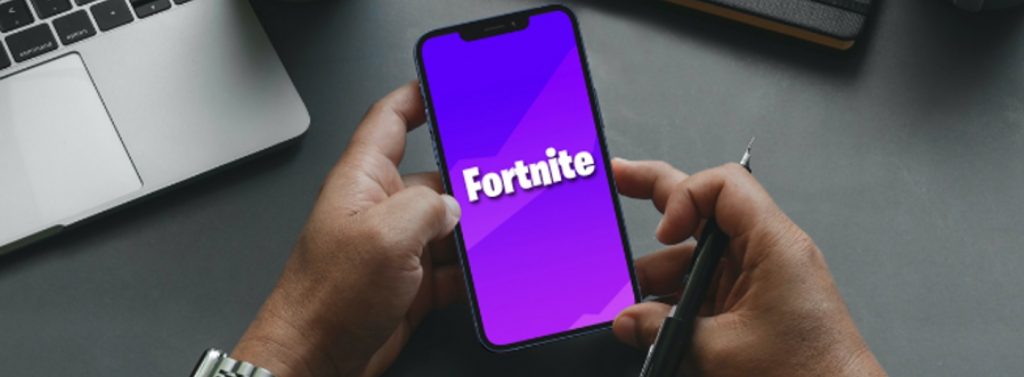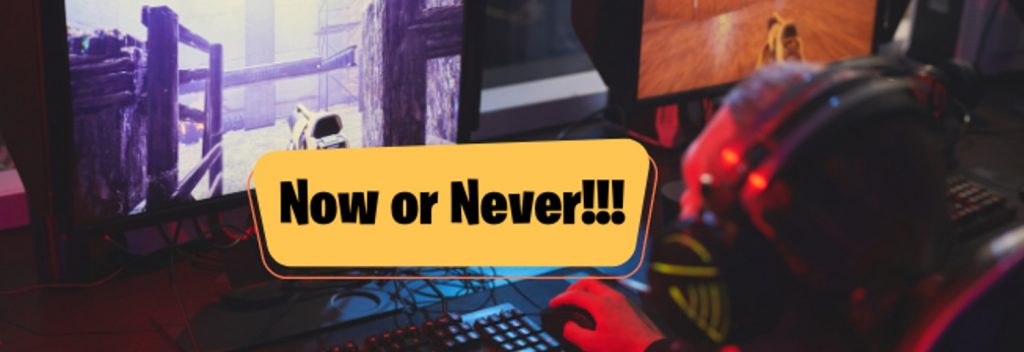
如何使用 Fortnite 字體創建漂亮的模型
已發表: 2022-11-22您是否多次聽到“Mockup”這個詞卻不知道這個詞的用途? 不要擔心,因為今天,我們將通過定義這個術語及其最佳字體來打破你的好奇心。 模型設計的成功在很大程度上取決於您所做的字體選擇。 字體越合適,您的設計就會越好。
在眾多選項中,我發現最完美的選項是 Fortnite,您以前可能也用過它。 本指南將討論有關此字體的所有重要因素。 除此之外,我們還將討論如何使用這種字體設計吸引人的模型。
什麼是模型設計?
模型是一種尚未發布的設計,只是一個樣本,用於展示最終產品在向公眾展示時的變化情況。 模型有多漂亮取決於您的專業知識。 您可以使用不同的可用軟件設計大量模型,包括 Photoshop 或 Adobe illustrator。 模型可以創建一個完整的網站,也可以是一個頁面。
他們最好的一點是,他們可以讓您自由地在需要的地方進行更改,因為一旦網站上線,就會出現並發症。 您還可以設計它們以在創建最終產品之前獲得公眾的反應。 它們被用於不同的領域,包括軟件開發、建築、消費品、家具等。
使用 Fortnite 字體製作模型
如果您是遊戲愛好者,您可能玩過 Fortnite 遊戲,該遊戲在發佈時獲得了所有好評。 2017 年,它被製作出來,超過 1 億人參與了該遊戲。 有了這次的成功,遊戲中使用的字體也獲得了讚賞,成為了大家的需求。 這款遊戲的標誌字體吸引了所有人的眼球,因為它很吸引人,並且具有吸引所有人注意力的力量。
經過研究,我們發現這款遊戲的標誌所使用的字體不是別人,正是Tal Leming多年前創造的Burbank Big Condensed。 而且,它是專門作為顯示字體創建的,非常適合這個原因。 它是一個大家族,有很多權重、樣式和字符,所以用在各種意義上的模型設計中都是很好的。
好吧,問題仍然存在,如何在看起來吸引人的設計中使用這種字體? 答案如下。
1. 將其用於品牌項目
假設您正在處理任何特定品牌,並且仍然對哪種字體最有希望用於模型設計感到困惑。 在這種情況下,您永遠不會被誤認為是 Fortnite 字體,因為它專門用於此驅動器。 它使品牌脫穎而出,人們不會停止重視您的工作。 這種字體為您的品牌帶來的優雅觸感也值得讚賞。
因此,如果你想開發一個立即吸引註意力的模型設計,我建議你在你的品牌作品中使用免費版本的 fortnite 字體,然後等待魔法。 這是您在排版方面獲得的最佳建議。
2.在徽標上使用此字體
眾所周知,Fortnite 在用於 Fortnite 視頻遊戲的徽標後積累了人氣。 因此,使用此字體的最佳方法是將其保存在重要的地方。 您可以將其保留在需要清晰的標題、徽標或有影響力的標題中。 這是您如何最好地使用這種字體。 在這種字體被淘汰後,許多設計師充分利用並在他們的設計中使用它,尤其是在標誌上。
同樣,如果您的品牌已準備好發布並且唯一的要求是徽標字體,請繼續使用 Fortnite,稍後您一定會感激您的決定。 這種 san-serif 字體提供清晰的可見性並吸引讀者關注您的設計。 在標題或徽標上使用此字體是將此字體用於精美模型設計的另一種最佳方式。
3.最適合遊戲平台
這種字體無疑是您的遊戲模型設計的最佳選擇,因為在 Fornite 遊戲發布後人們開始了解它,並且每個人都為之瘋狂。 如果你有一個遊戲網站,你不應該再考慮這種字體是否適合設計。 去吧。 充分利用這個大字體系列,讓結果對您有利。
4.根據設計心情選擇
選擇一種完美無瑕的字體非常適合設計氛圍,因為如果您的字體不能與設計相得益彰,那麼您的模型將是最大的失望。 作為一名設計師,你必須知道哪種字體適合不同類型的設計,並通過實踐,成為這項技能的高手。 Fortnite 字體的主要品質之一是它適合不同的心情; 這就是為什麼在不同的設計中使用它之前不需要考慮太多。
如果你想讓你的 Mockup 設計成功,必須注意這一點,以便讀者在檢查你的設計時順其自然。
5.注意配對
配對對於成功的設計也很重要,所以一定要做好。 在一個設計中,你至少需要 2 或 3 種字體,所以它們都應該非常適合,這樣它們看起來才不會很奇怪。 該遊戲徽標上使用的字體與擴展的 Burbank Big 字體家族相同,因此您一定會得到類似的字體。
此外,它是一種 san-serif 字體,因此您還可以找到除此 Fortnite 字體系列之外的一些字體。 不要過度使用字體,因為它會降低質量,讀者在檢查設計時肯定會感到困惑和最不感興趣。 這些關於你的模型設計的小細節應該永遠記住,以避免將來出現任何大麻煩。
6.可讀性分數很強大
每當你談論排版時,可讀性分數總是會出現,因為兩者是相輔相成的。 請放心,讀者永遠不必爭論您的設計的可讀性低; 否則,你的設計將是一種浪費。 設計的大小,從上到下都應該承認,不能有一點在理解上不明顯。
它是網站成功的關鍵因素,特別關注這一點的設計師永遠不會失敗。 這一點也不應被忽視。 Fortnite 可讓您的模型設計清晰易讀。
7.設計的一致性
設計不僅僅是關於字體,因為許多其他元素也會有所不同。 每個元素和點都應該適當地調整到設計中,這樣就不會顯得凌亂。 字體、間距和對齊之間應該保持一致。 當您深入關注每個點而不是將重點轉移到單個事物上時,設計就會成功。
您選擇的其他兩種字體必須使所有內容保持一致,以使其看起來令人耳目一新和吸引人。 這就是您如何開發吸引觀眾的網站。
8. 選擇字體時要挑剔
各種設計師在選擇字體之前都不會費心去搜索,而是使用他們在每個設計中都使用的標準字體,包括 Helvetica 字體和 Futura 字體。 這是他們最大的錯誤,因為設計師在為設計選擇任何字體時都必須挑剔。
最後的想法
每個設計師都知道模型設計的重要性。 它們可能不是原始產品,但這是了解客戶對您網站的看法以及您如何形成可愛設計的好方法。 在創建一個可愛的設計時,字體對你有很大幫助,所以要付出額外的努力來尋找它們,這樣結果才會公平。 如果您正在努力尋找一種適合您的模型設計的選項,那麼 Fortnite 字體是最有前途的選擇。
本文清楚地講述了該字體的詳細信息,以便您了解為什麼該字體具有巨大的意義以及為什麼它應該包含在您的下一個設計項目中。 希望這足以說服您,現在最終決定權在您。